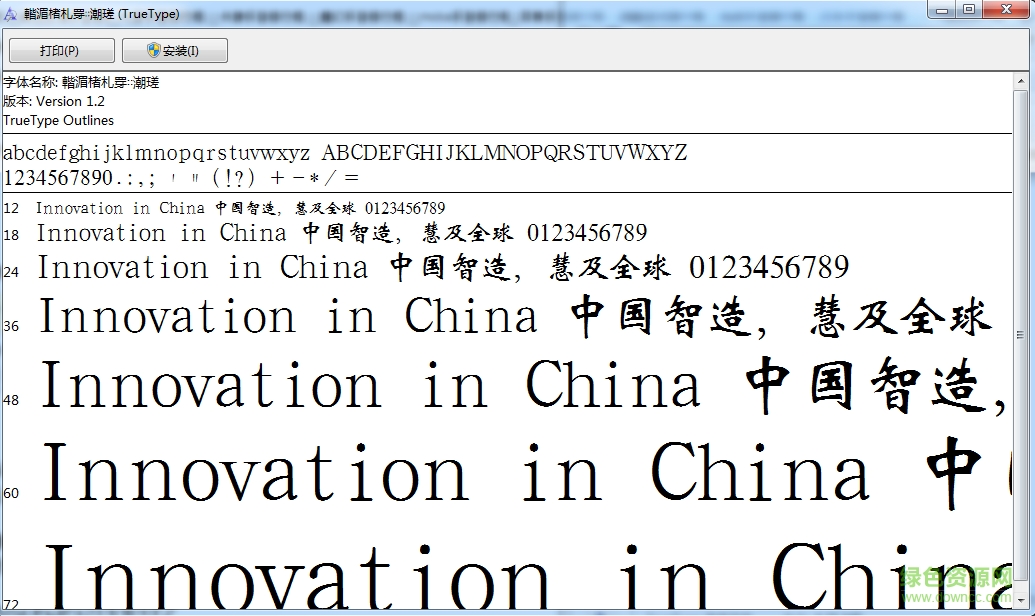
漢鼎簡(jiǎn)魏碑是一款字跡簡(jiǎn)潔大方的魏碑簡(jiǎn)體字體,端正秀麗的字形一直很受文人墨客們的追捧,綠色資源網(wǎng)為大家?guī)?lái)免費(fèi)版本,歡迎需要的朋友下載體驗(yàn)!
魏碑是指南北朝時(shí)期北朝的碑刻書法作品?,F(xiàn)存的魏碑書體都是楷書,因此有時(shí)也把這些楷書碑刻作品稱為“魏楷”。魏碑原本也稱北碑,在北朝相繼的各個(gè)王朝中以北魏的立國(guó)時(shí)間最長(zhǎng),后來(lái)就用“魏碑”來(lái)指稱包括東魏、西魏、北齊和北周在內(nèi)的整個(gè)北朝的碑刻書法作品。這些碑刻作品主要是以“石碑”、“墓志銘”、“摩崖”和“造像記”的形式存在的。